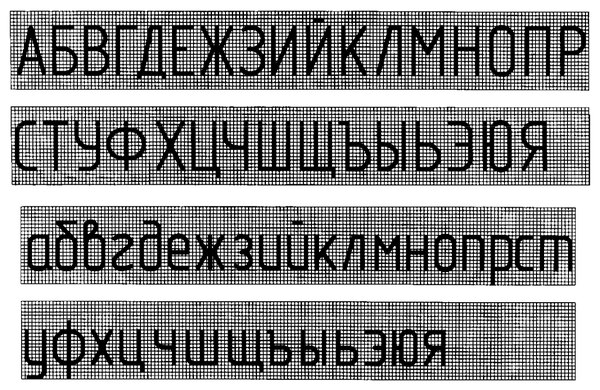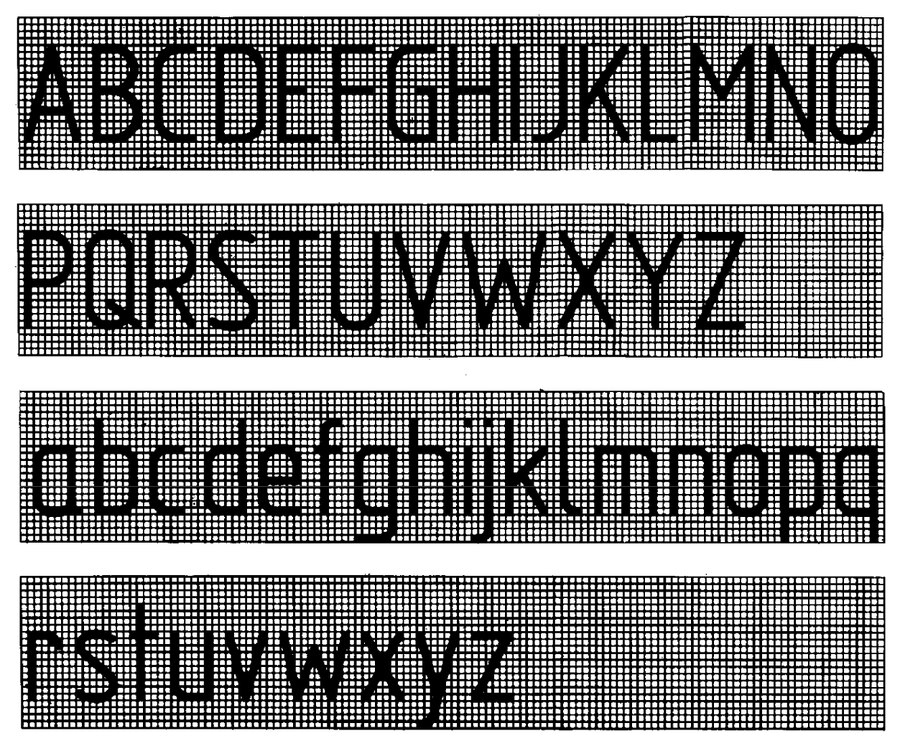
Если вам приходиться чертить схемы по ГОСТ то, наверное, знаете, что во всех чертежах для нанесения надписей используются специальные чертежные шрифты.
Чертежные шрифты устанавливает ГОСТ 2.304–81. В состав чертежных шрифтов входит русский, латинский и греческий алфавиты, арабские и римские цифры, а также знаки.
ГОСТ 2.304–81 устанавливает четыре типа шрифтов:
тип А без наклона
тип А с наклоном около 75°;
тип Б без наклона;
тип Б с наклоном около 75°
Размер шрифта h определяется высотой прописных букв (в мм). ГОСТ 2.304 — 81 устанавливает следующие размеры шрифтов: 2,5; 3,5; 5; 7; 10; 14; 20; 28; 40.
| Прописные буквы и цифры Высота букв и цифр Ширина букв Г, Е, 3, С и цифр 2, 3, 5, 6, 7, 8, 9, 0 Ширина букв Б, В, И, И, К, Л, Н, О, П, Р, Т, У, Ц, Ч, Ь, Э, Я и цифры 4 Ширина букв А, Д, М, X, Ы, Ю Ширина букв Ж, Ф, Ш, Ъ Ширина цифры 1 Строчные буквы Высота букв, кроме в, д, р, у, ф Высота букв б, в, д, р, у, ф Ширина букв, кроме ж, з, ч, с, т, ф, ш, щ, ъ, ы, ю Ширина букв з, с Ширина букв м, ъ, ы, ю Ширина букв т, ж, ф, ш Расстояние между буквами и цифрами Расстояние между основаниями строк Минимальное расстояние между словами Толщина линий шрифта | h g g g g с с g g g g а b е d | (10/10) h (5/10) h (6/10) h (7/10) h (8/10) h (3/10) h (7/10) h (10/10) h (5/10) h (4/10) h (6/10) h (7/10) h (2/10) h (17/10) h (6/10) h (1/10) h | 10d 5d 6d 7d 8d 3d 7d 10d 5d 4d 6d 7d 2d 17d 6d 1d | 3,5 1,7 2,1 2,4 2,8 2,0 2,5 3,5 1,7 1,4 2,1 2,4 0,7 6,0 2,1 0,35 | 5,02,5 3,0 3,5 4,0 1,5 3,5 5,0 2,5 2,0 3,0 3,5 1,0 8,5 3,0 0,5 | 7,0 3,5 4,2 4,9 5,6 2,1 5,0 7,0 3,5 2,8 4,2 4,9 1,4 12,0 4,2 0,7 | 10,0 5,0 6,0 7,0 8,0 3,0 7,0 10,0 4,0 6,0 70 2,0 17,0 6,0 1,0 |
Приложение 2 Чертежный шрифт с наклоном по ГОСТ 2. 304—68
Размеры шрифта (высота прописных букв) h 2,5 3,5 5 7 10 14 20 28 40 (в миллиметрах). [c.311]
Толщина линии шрифта d — зависит от типа и высоты шрифта (соответствует шагу вспомогательных линий сетки) [c.311]
Шрифт типа Б с наклоном около 75° (d— / (10А) [c.311]
Установлен шрифт типа Б и без наклона. Шрифт типа А без наклона и с наклоном имеет d— 1/14 (суженный, но конструкция, начертания аналогичные)
Глава II. Выполнение чертежного шрифта [c.9]
ГОСТ 2.304—81 устанавливает чертежные шрифты, наносимые на чертежи и другие технические документы всех отраслей промышленности и строительства. [c.9]
Толщина линии шрифта d зависит от типа и высоты шрифта. [c.9]
ГОСТ устанавливает следующие размеры шрифта (1,8) 2,. ) 3,5 5 7 10 14 20 (табл. 2, 3). Применение шрифта 1,8 не рекомендуется и допускается только для типа Б. [c.9]